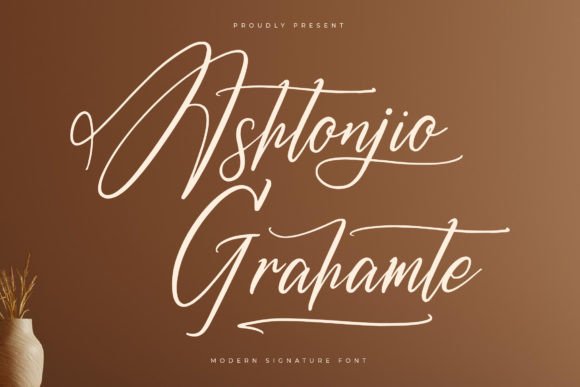
Ashtonjio Grahamte
Jika anda sedang mencari aset berkualiti tinggi seperti Ashtonjio Grahamte, pakej premium ini merupakan pilihan yang hebat untuk projek kreatif anda.
Dicipta dengan ketepatan, Ashtonjio Grahamte menyediakan vektor yang bersih, tipografi yang licin dan lesen komersial untuk ketenangan fikiran.
Sama ada anda mencipta produk POD (Print on Demand), jemputan perkahwinan atau grafik media sosial, Ashtonjio Grahamte amat bersesuaian.